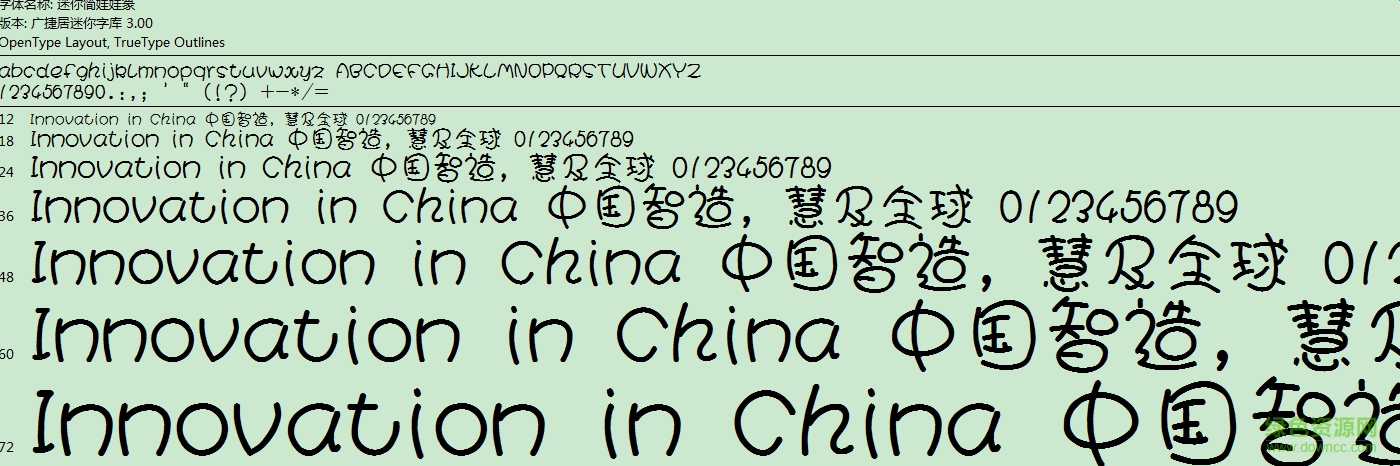
jwawazuan字體又叫迷你簡娃娃篆,是一款非常萌的迷你字體,字形獨特,圓圓滾滾,就像熊貓小團子一樣,廣告效果非常好,特別適合女性用戶們在編輯文字時使用,非常的實用,喜歡這款字體的小伙伴快來下載吧!
大篆:廣義指'小篆'以前的文字和書體,包括甲骨文、鐘鼎文、籀文和六國文字等;狹義專指周宣王太史籀厘定的文字,即'籀文'。
小篆:篆書之一,與'大篆'對稱。亦稱'秦篆',意指秦始皇統(tǒng)一天下文字而命李斯所制也。小篆筆劃圓轉流暢,較大篆整齊。